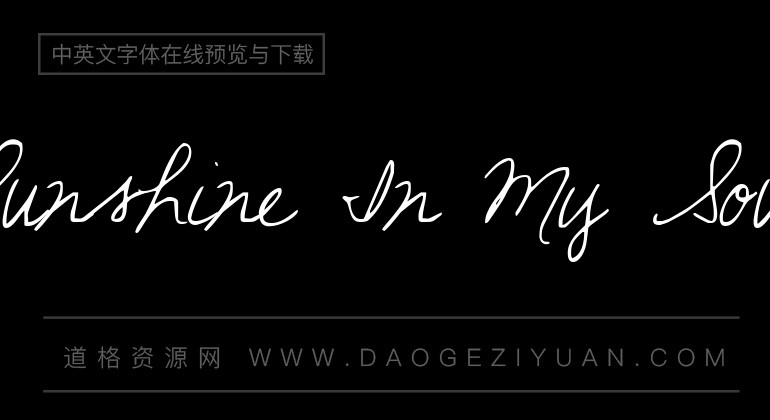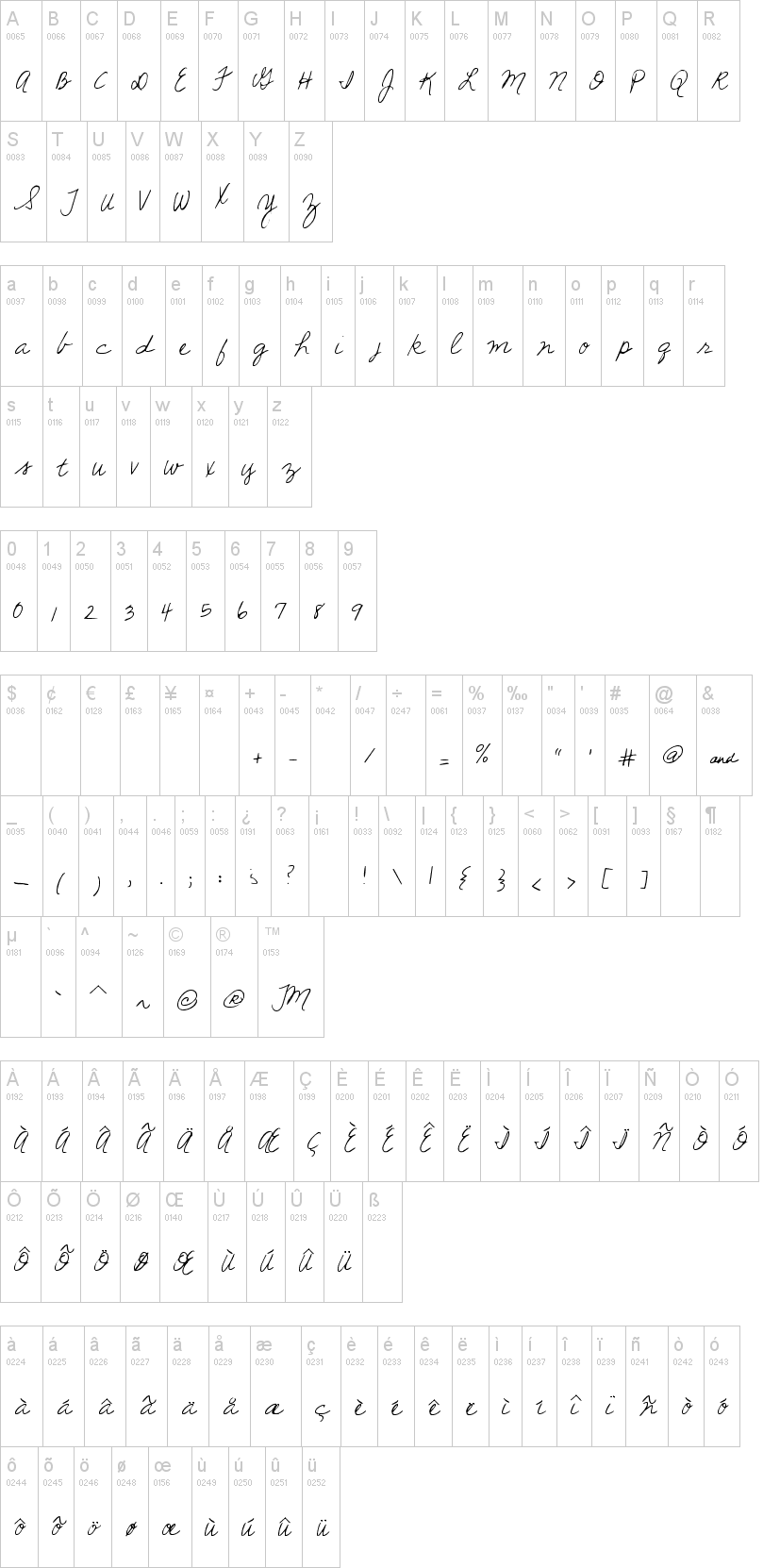
Sunshine In My Soul 是一款字体,由英国设计师Jason Walcott设计,它是一款简单、现代化的字体,可以在任何场景中使用,尤其适合用于标题、标语等。它有一种温暖、活泼的感觉,可以让文字充满活力,同时又能保持简洁、优雅的风格。Sunshine In My Soul字体可以在所有的操作系统上使用,包括Windows、Mac OS X和Linux等。内容介绍
Sunshine In My Soul是一款非常不错的手写艺术字体,具有很好的视觉感,适合于文化类的宣传设计、商业类品牌的广告和产品包装设计以及个性化文字排版等较多场景。